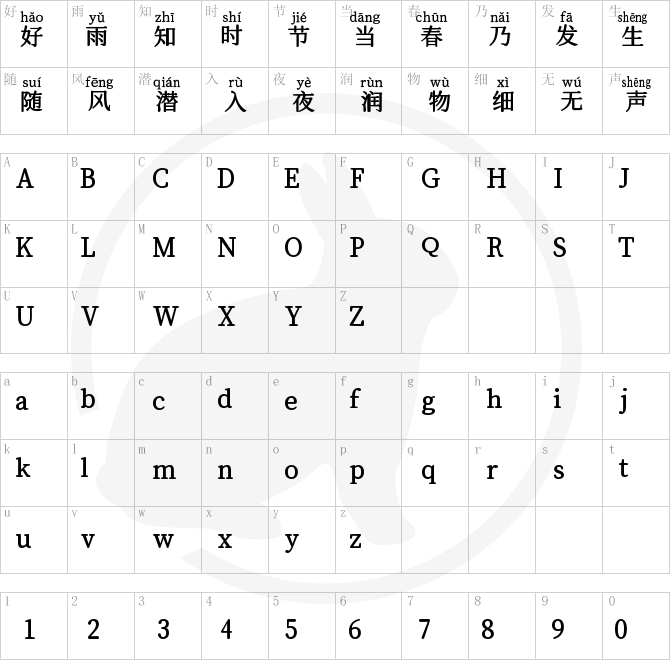
YEFONTFangSongPinYin 標準
YEFONTFangSongPinYin 標準,这款字体结构工整、笔画清晰,兼顾美观与易读性,适用于标题、正文、海报、包装、LOGO 等多种场景。字形优雅稳定,风格百搭耐看,适配日常排版与创意设计,让文字呈现更舒适、更具质感。YEFONTFangSongPinYin 標準一笔一画,皆是细节,以均衡的比例、流畅的线条打造舒适视觉体验,字形端正大气,风格简约现代。无论是商业设计、品牌宣传还是日常排版,都能轻松驾驭,让文字更有格调与力量。YEFONTFangSongPinYin 標準字体下载。